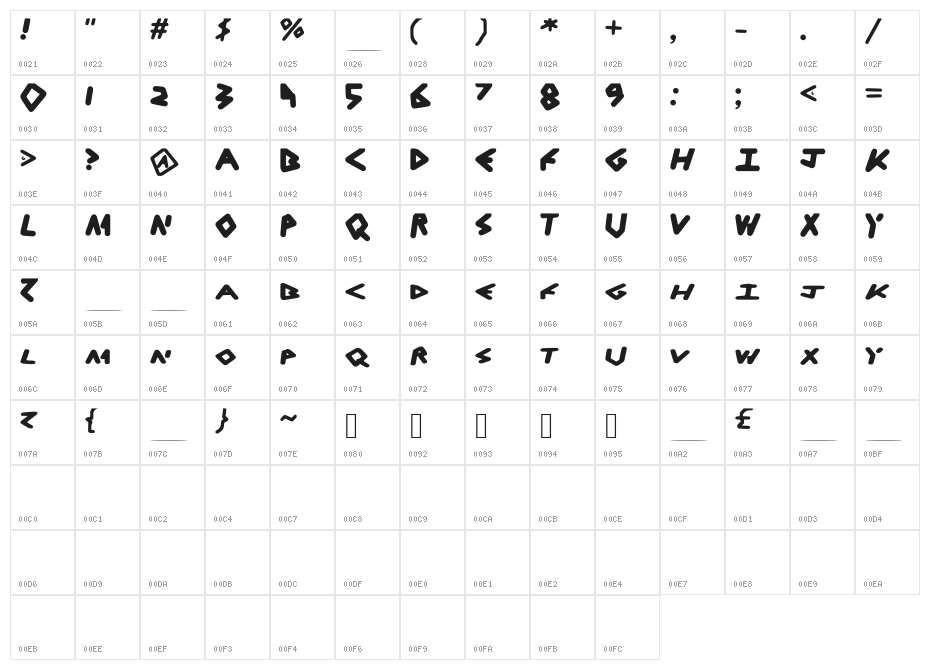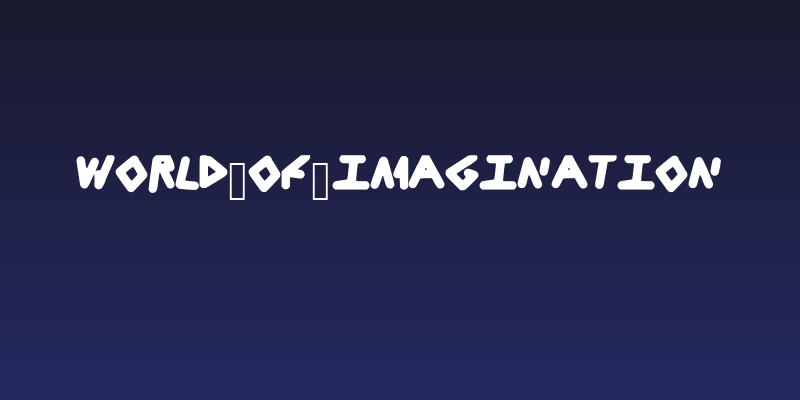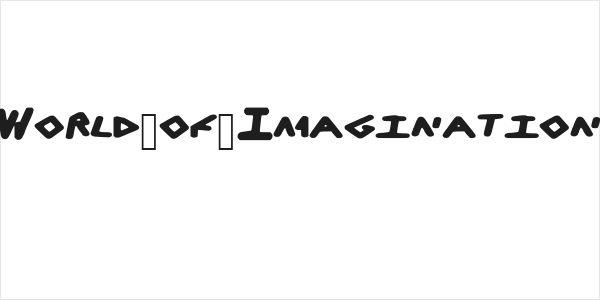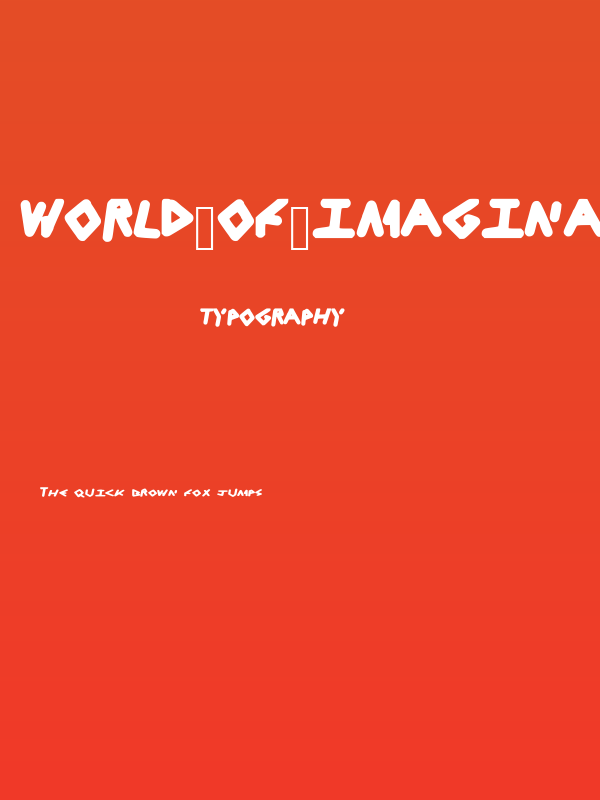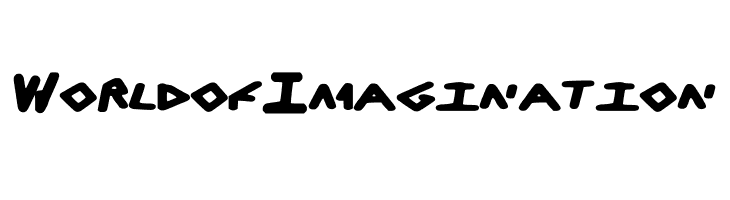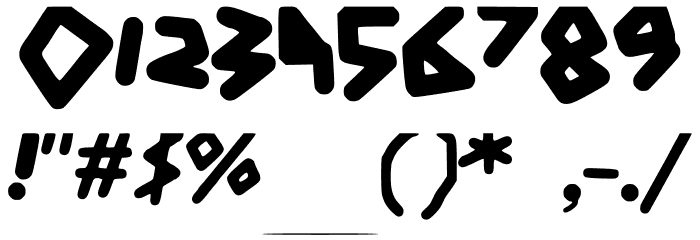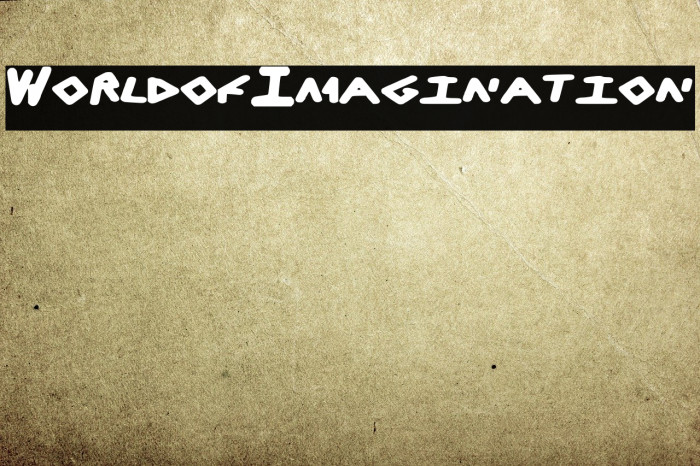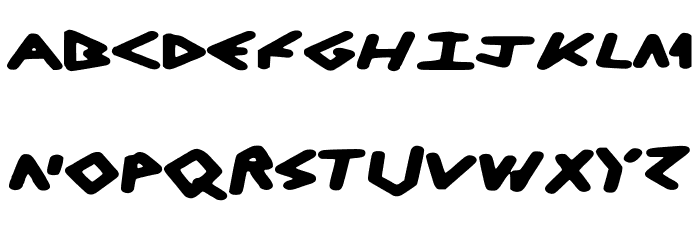
World_of_Imagination Font
| Общий стиль | Playful, Whimsical |
| Рекомендуемые проекты | Ideal for children's books, playful branding, creative posters, and eye-catching headlines. |